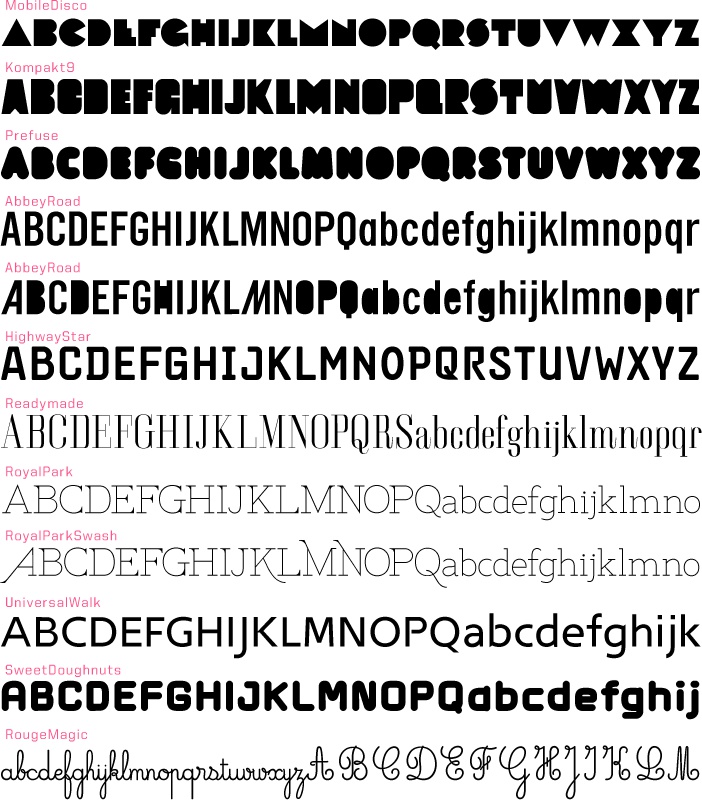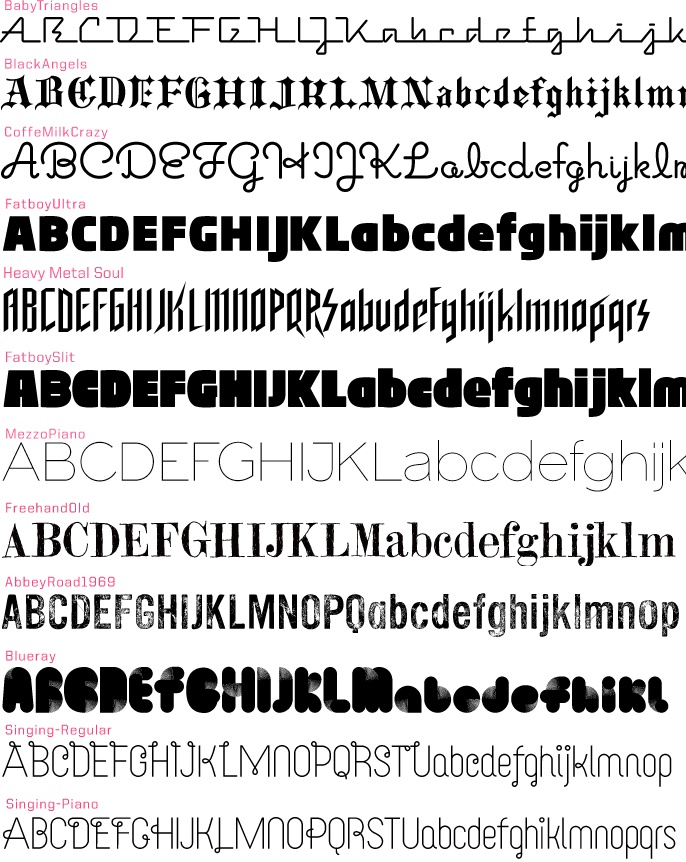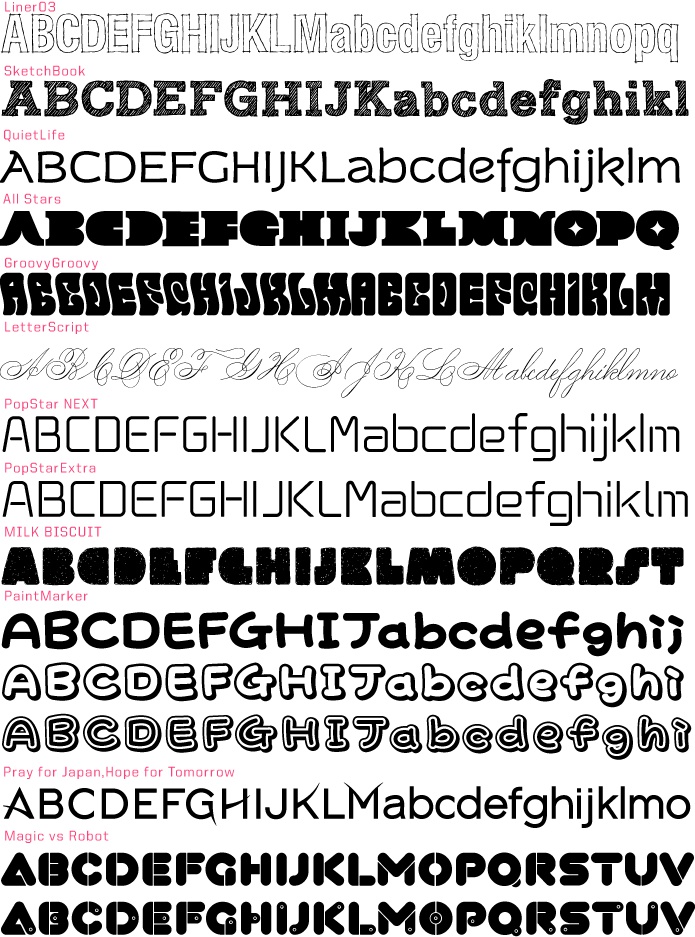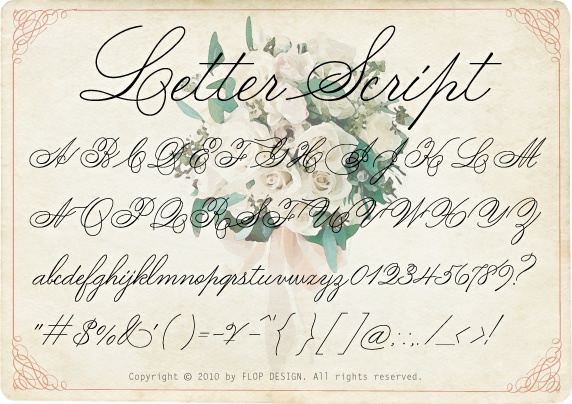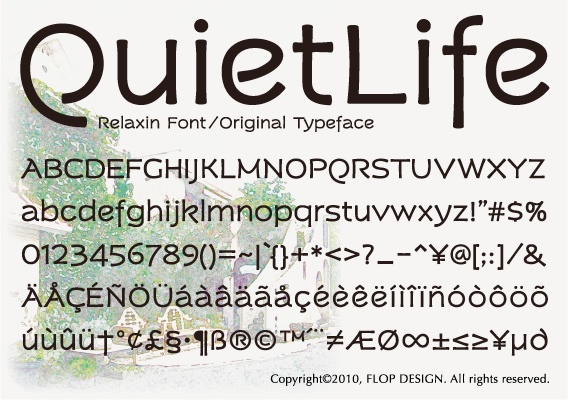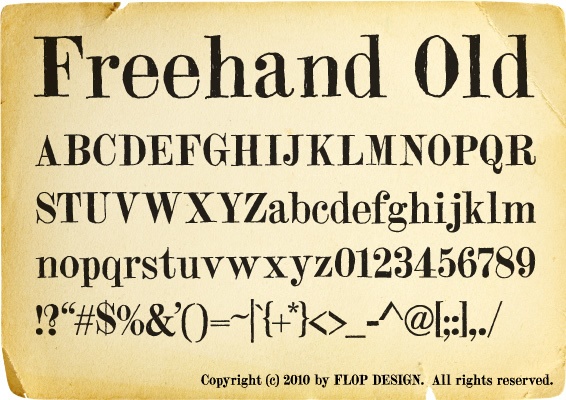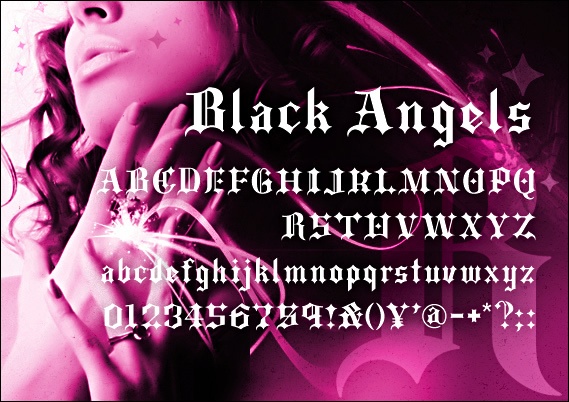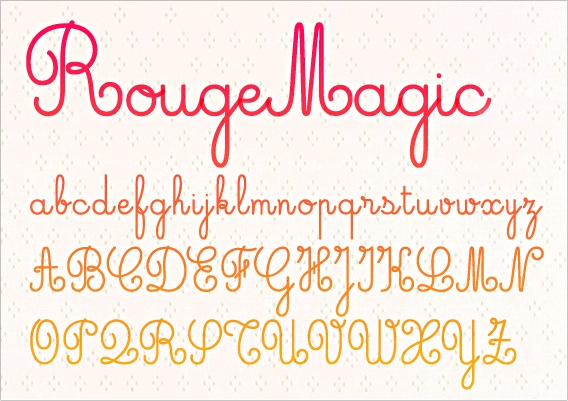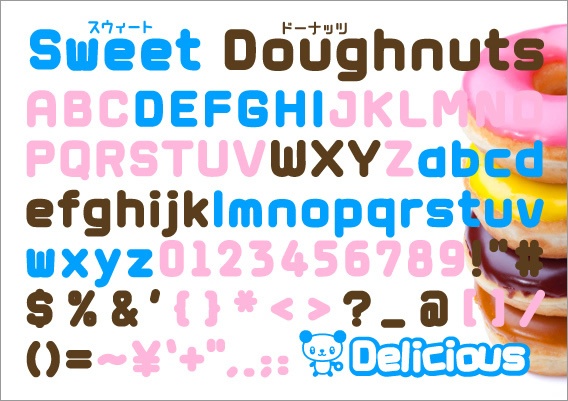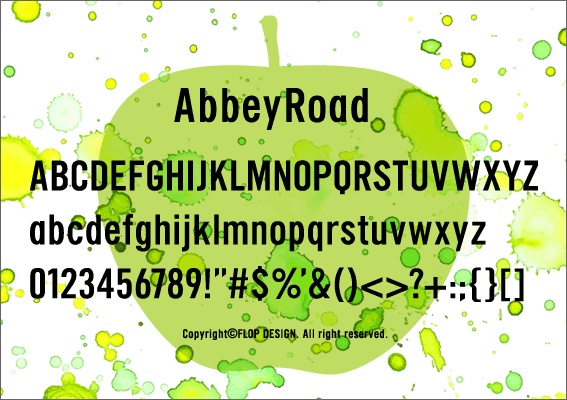
最先端のスタイリッシュな商用利用可の欧文フォント集 スタイリッシュ!そう呼ぶのにふさわしい欧文フォント集のダウンロード販売。最新型のデザインフォントはクール からキュートまで様々な用途に威力を発揮するものばかりです。さあ、あなたのセンスでこのアルファベット達を活用して下さい。きっとデザインライフはますます楽しいものになるはずです。最先端のデザインに適した、このフォント集ならではオリジナルのタイプフェイスを手に入れてください。 推奨動作環境 Mac:OS X対応(10.x)~最新のOS Windows:OS/日本語版Windows2000、XP、VISTA、Windows7〜11以降 フォント形式:Macintosh用TrueType、OpenType・Windows用TrueType、OpenType ・Adobeイラストレーター、フォトショップはもちろんのことエクセル等でもご使用になれます。 収録フォントについて MobileDisco、 AbbeyRoad-Alternative、HighwayStar、Kompakt9、AbbeyRoad、Prefuse、Readymade、 RoyalPark、RoyalPark-Swash、UniversalWalk、RougeMagic、SweetDoughtnuts、 BabyTriangles、BlackAngels、CoffeeMilkCrazy、FatboyUltra、HeavyMetalSoul、 FatboySlit、MezzoPiano、FreehandOld、AbbeyRoad1969、Blueray、Singing-Regular、 Singing-Piano、Liner03、SketchBook、QuietLife、All Stars、GroovyGroovy、LetterScript、PopStarNEXT、PopStarExtra、Milkbiscuit、 PaintMarker、Pray for japan,Hope for Tomorrow、Magic vs Robot等の39フォントになります。フォントファイルはOPEN TYPEになります。旧OS用にTrueTypeフォントも同梱しています。 収録文字数について アルファベット、記号のみの欧文フォントになります。Prefuse、MobileDisco、 Kompakt9、All Stars、Magic vs Robotにはデザイン性質上、小文字・数字が含まれていません。 安心して使えるロイヤリティフリーの書体 あらゆる商用・デザイン用途(印刷物・ゲーム・アプリ・映像・動画・ロゴ・同人作品)に使用できる、商用申請の必要のないロイヤリティフリーの書体になります。文字の加工・変形も可能です。ご安心ください。